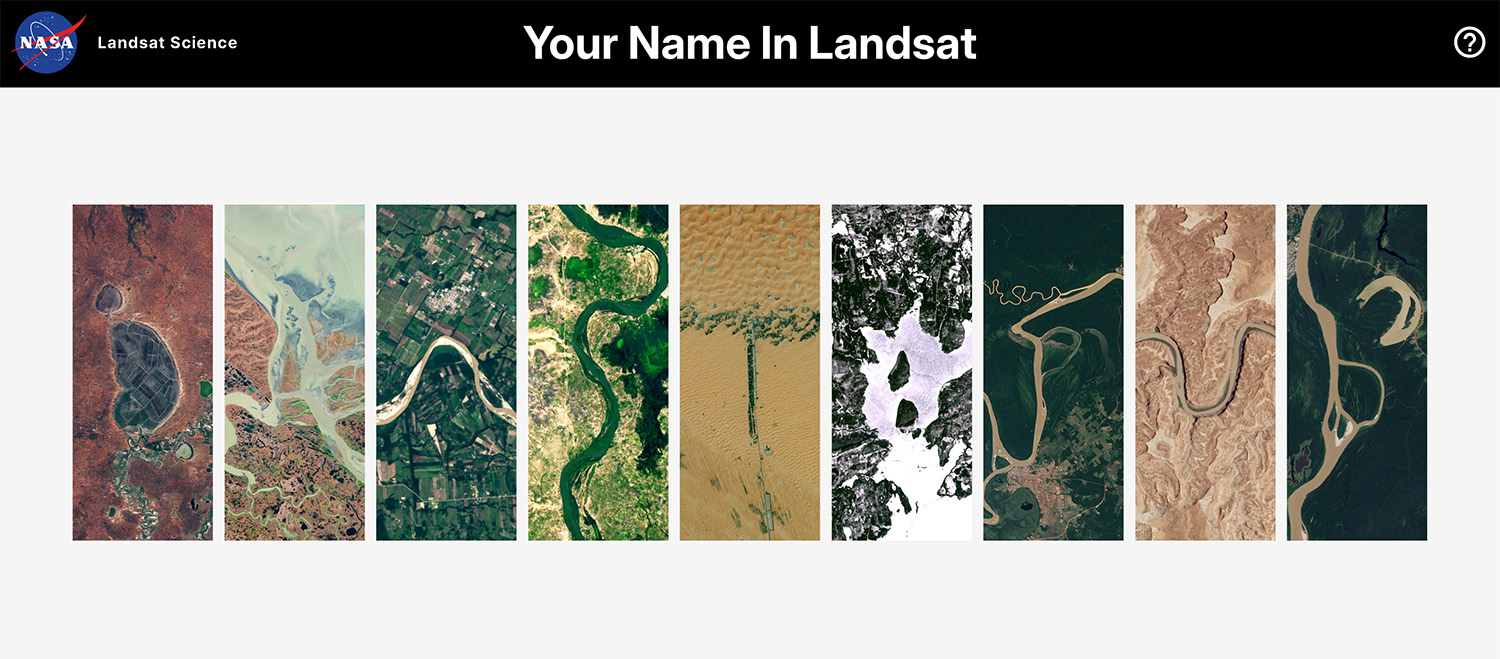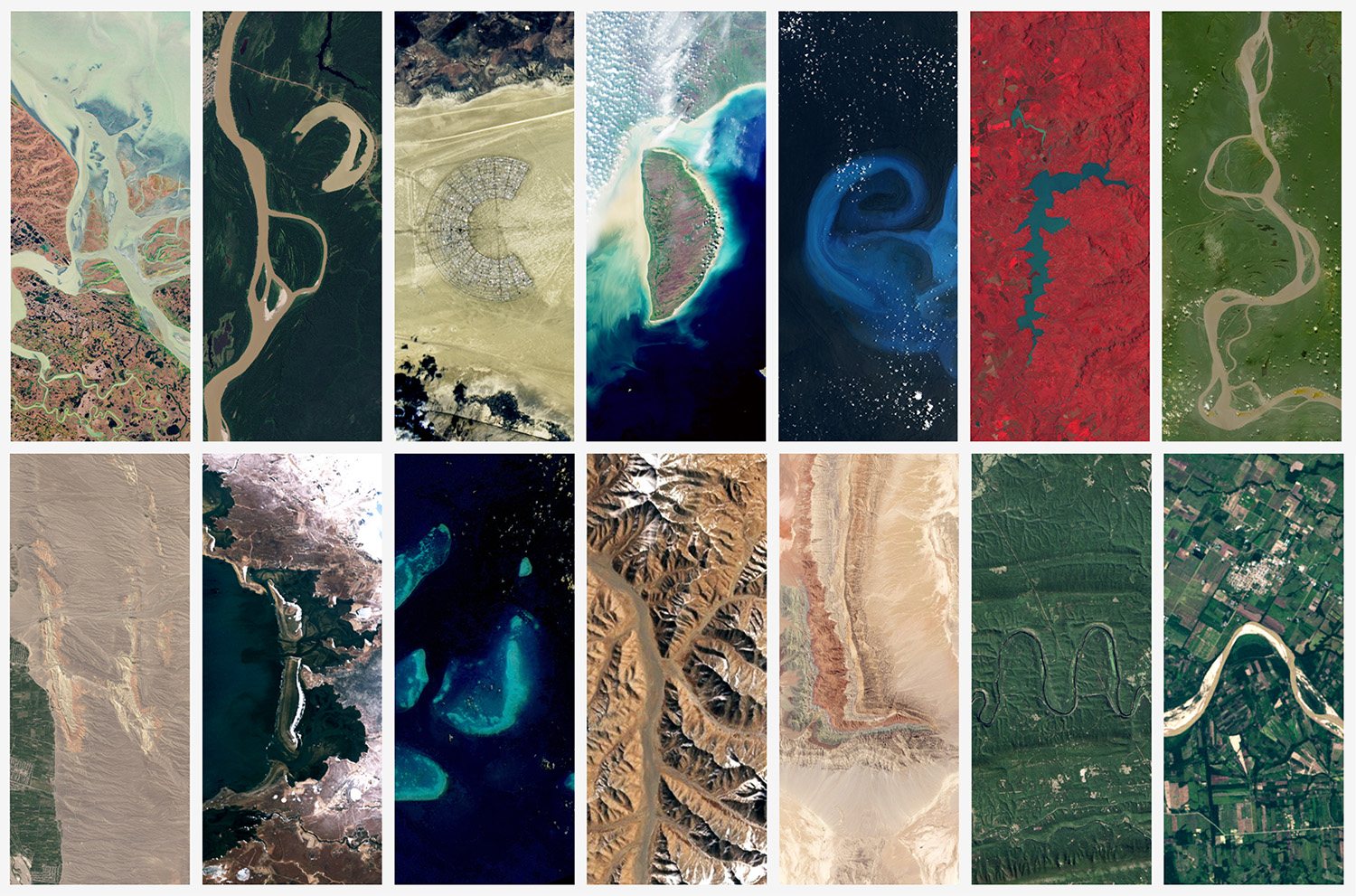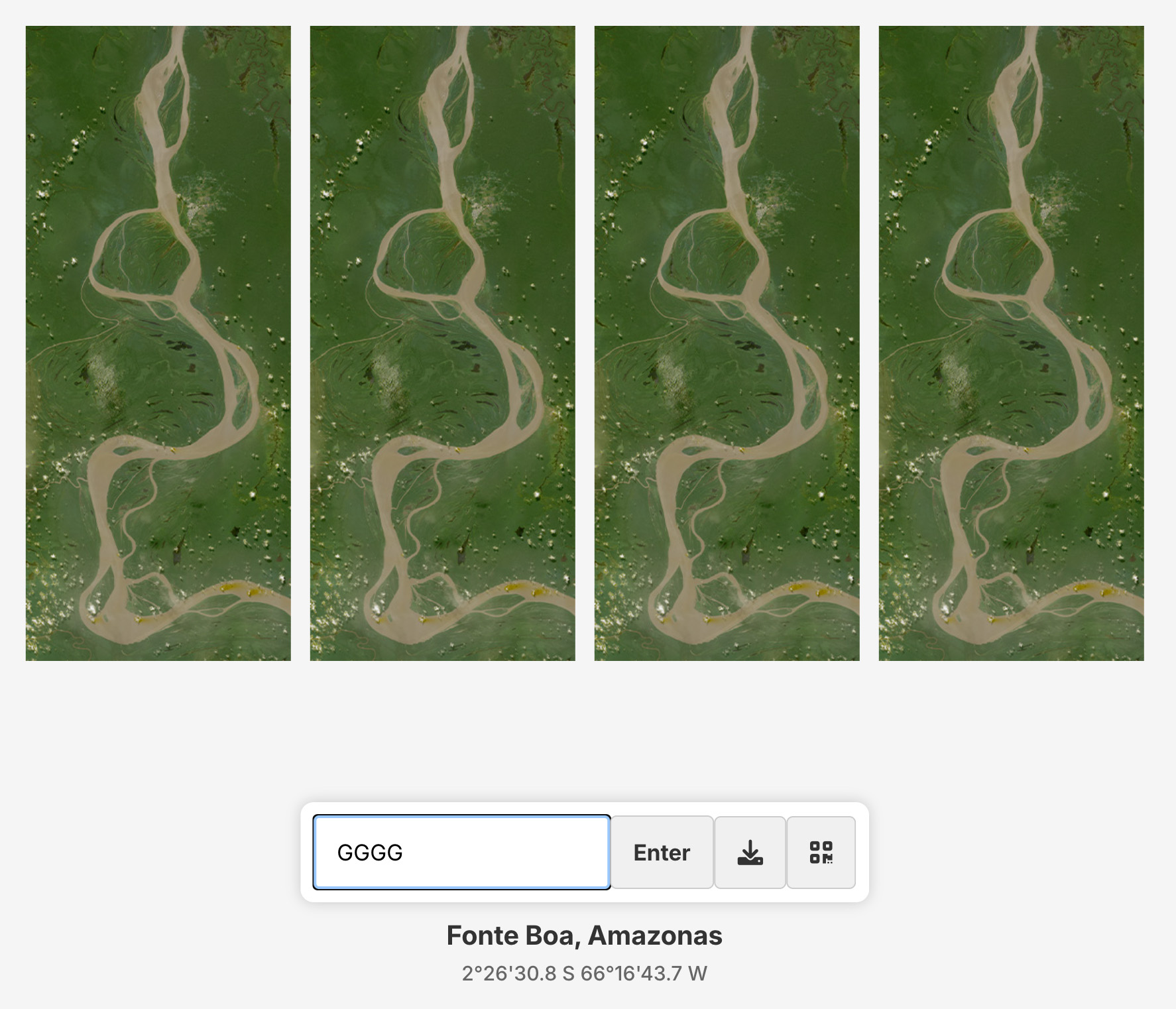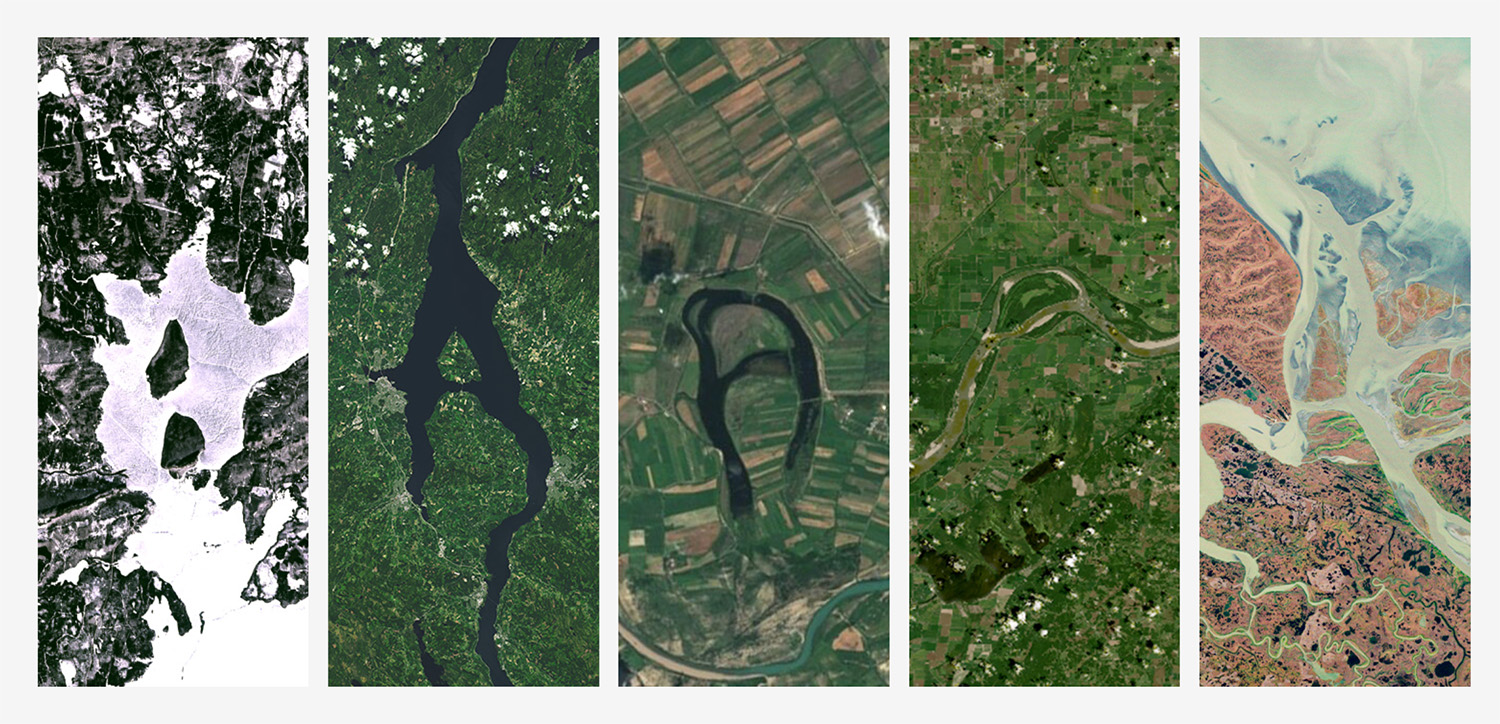
La NASA continue d’explorer les ponts entre la rigueur scientifique et la créativité visuelle. À l’occasion de la Journée de la Terre, le Centre spatial Kennedy a mis en avant un outil numérique singulier : « Votre nom en Landsat ».
Ce générateur permet d’écrire n’importe quel mot en utilisant une typographie entièrement constituée de paysages terrestres capturés depuis l’espace. En transformant des rivières, des lacs et des formations géologiques en caractères alphabétiques, l’agence spatiale propose une immersion pédagogique dans l’observation satellite.
Un héritage de données transformé en expérience interactive
Si l’outil bénéficie aujourd’hui d’un regain de popularité, son origine remonte à août 2014. Il avait été initialement conçu pour le Camp Landsat, un programme pédagogique estival. Ce projet s’appuie sur les archives monumentales du programme Landsat, la mission d’observation de la Terre la plus longue de l’histoire. Lancée en 1972, elle cumule plus de 50 ans de données cartographiques et environnementales.
L’enjeu de cette plateforme dépasse le simple gadget visuel. Elle traduit une masse de données scientifiques complexes en un langage universel. En interagissant avec l’interface, l’utilisateur accède à la localisation précise et aux coordonnées de chaque cliché. C’est une manière pour la NASA de valoriser un patrimoine technologique souvent méconnu du grand public, tout en illustrant l’évolution de notre planète sur plusieurs décennies.
La typographie comme outil de médiation géographique
Le fonctionnement du générateur repose sur une base de données d’images satellites où chaque lettre est associée à une forme naturelle. Le système révèle des disparités intéressantes sur la morphologie du globe. Par exemple, la lettre « A » dispose de cinq variations distinctes, issues du delta du Yukon en Alaska ou du lac Guakhmaz en Azerbaïdjan. À l’inverse, d’autres caractères sont beaucoup plus rares dans la nature.
La lettre « G » ne dispose actuellement que d’une seule représentation iconographique, capturée à Fonte Boa, dans l’État d’Amazonas au Brésil. Cette rareté souligne la complexité de l’exercice : trouver dans le chaos géologique des structures qui répondent aux codes de notre alphabet. Pour la NASA, cette approche permet de sensibiliser aux enjeux de la gestion des ressources naturelles et de la planification environnementale en rendant les clichés satellites concrets et ludiques.
Du contenu scientifique au phénomène culturel global
L’accueil réservé à cette initiative témoigne d’un intérêt croissant pour le branding territorial et l’utilisation de la donnée comme matière première créative. En moins d’une semaine, la publication originale a franchi le cap des 50 millions de vues sur les réseaux sociaux. Ce succès a même incité des marques comme Xbox à s’approprier l’outil pour diffuser leurs propres messages, transformant ainsi une ressource scientifique en un contenu culturel participatif.
Cette stratégie s’inscrit dans une tendance de fond où les institutions utilisent l’imagerie satellite pour construire des récits territoriaux forts. L’exemple de la marque Amazonie brésilienne est probant : le territoire n’est plus un simple décor, mais devient le fondement même de l’identité graphique. En démocratisant l’accès à ces images, la NASA ne se contente pas de montrer la Terre ; elle invite le public à se l’approprier, renforçant ainsi la portée de ses missions d’observation.